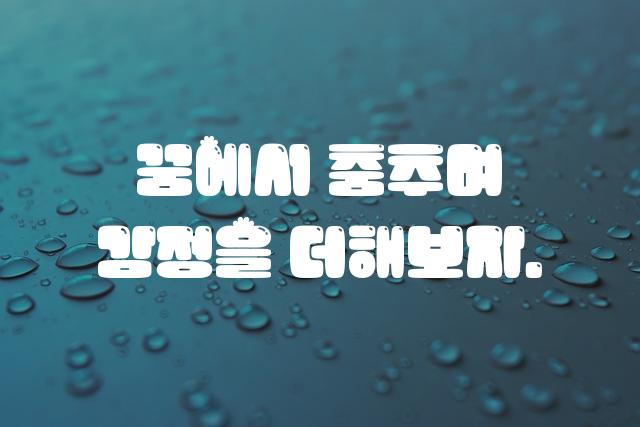
읏맨체는 OK금융그룹에서 제작한 독특하고 두꺼운 붓글씨 스타일의 폰트입니다. 레트로 감성과 각진 장식체 디자인이 특징적으로 어우러져, 과거와 현대의 조화를 느낄 수 있습니다.
읏맨체은(는)
별모양/패턴, 손글씨, 단단함, 복고풍, 감성적인, 네모꼴, 장식 스타일, 펜/붓터치, 굵은 고딕, 두꺼운 스타일, 레트로 계열의 생김새를 가지고 있으며
소셜 미디어, 어린이 책, 포스터 등에서 자주 활용되며, 효과적인 메시지 전달에 적합합니다.
이 폰트는 엔터테인먼트, 문화/예술, 출판/미디어 분야에 잘 어울리며,
재미있는, 귀여운, 친근한 느낌을 담고 있는 것이 특징입니다.
이 폰트와 유사한 폰트로는 한나체, 연성체, 넥슨 임팩트 등이 있어요. 함께 비교해 보시면 좋습니다!